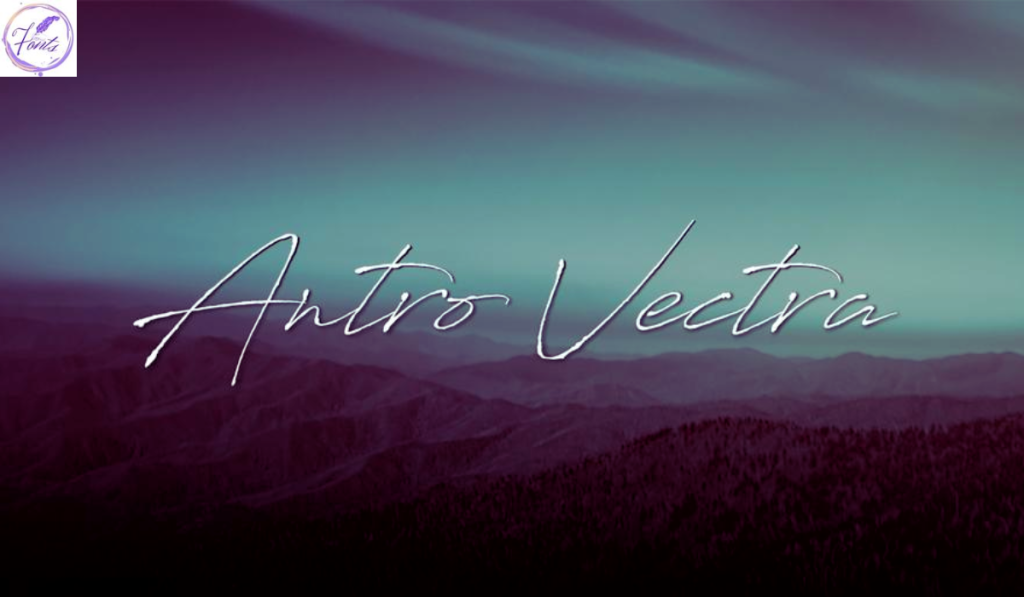
Antro Vectra font việt hóa
Tác giả: Youssef Habchi
Ngày phát hành: 2017
Ngôn ngữ: Tiếng Việt, Tiếng Anh, và nhiều ngôn ngữ khác
Bộ Font: Antro Vectra
Phân loại: Cá tính, độc đáo
Kiểu chữ: Kiểu chữ viết tay
Độ dày: Antro Vectra Regular, Antro Vectra Bolder
Antro vectra font là một bộ font chữ việt hóa mang phong cách hiện đại và độc đáo. Được phát triển bởi nhà thiết kế nổi tiếng Youssef Habchi vào năm 2017, antro vectra font nhanh chóng trở thành lựa chọn hàng đầu của nhiều nhà thiết kế đồ họa và nhà phát triển web. Bộ font này không chỉ mang lại sự mới mẻ trong cách trình bày văn bản mà còn giúp tạo nên những sản phẩm thiết kế đầy ấn tượng và cá tính.
Đánh giá antro vectra font
Antro vectra font nhận được sự khen ngợi từ nhiều chuyên gia trong ngành thiết kế nhờ vào khả năng ứng dụng linh hoạt và vẻ đẹp tinh tế. Nhà thiết kế đồ họa Trần Minh đánh giá cao sự sáng tạo và tính thẩm mỹ của bộ font này. Đặc biệt, antro vectra font còn được tối ưu hóa cho các dự án in ấn và thiết kế kỹ thuật số, giúp nâng cao chất lượng sản phẩm và tiết kiệm thời gian cho người sử dụng.